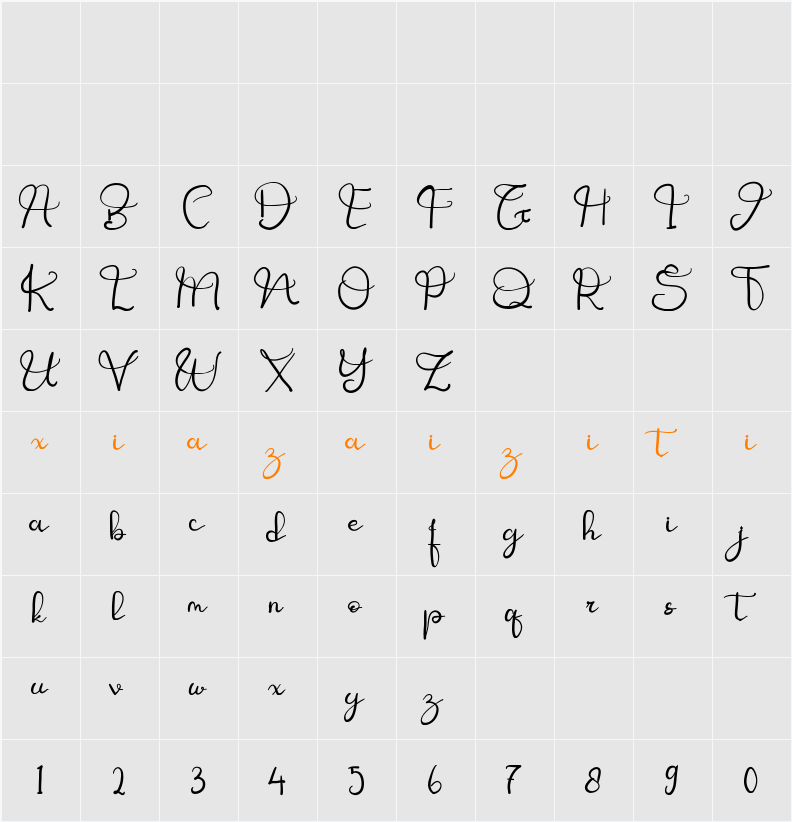
Zumanji Valkalari
Zumanji Valkalari,这款字体结构工整、笔画清晰,兼顾美观与易读性,适用于标题、正文、海报、包装、LOGO 等多种场景。字形优雅稳定,风格百搭耐看,适配日常排版与创意设计,让文字呈现更舒适、更具质感。Zumanji Valkalari一笔一画,皆是细节,以均衡的比例、流畅的线条打造舒适视觉体验,字形端正大气,风格简约现代。无论是商业设计、品牌宣传还是日常排版,都能轻松驾驭,让文字更有格调与力量。Zumanji Valkalari字体下载。